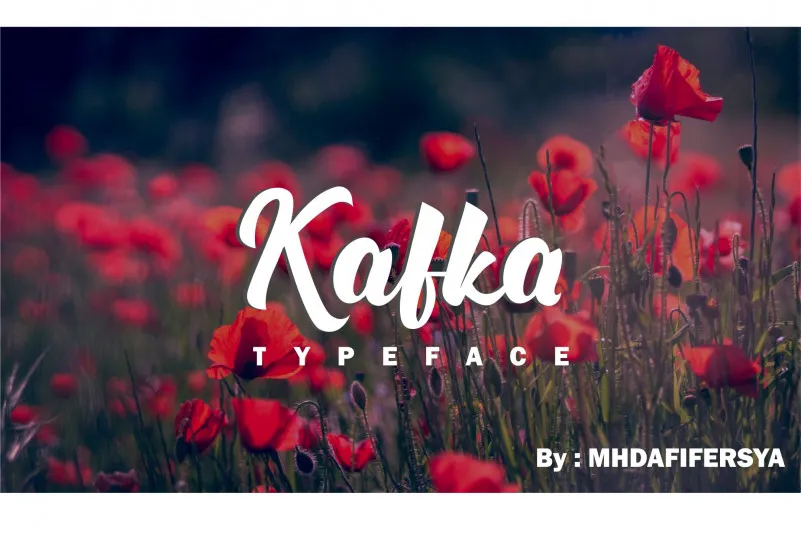
Kafka Script Font é uma tipografia em estilo script que se destaca pela sua força e elegância. Desenvolvida pelo designer mhdafifersya, ela se apresenta como um tipo de tipo com aparência limpa e rústica. Ideal tanto para criação de logotipos quanto para design de materiais promocionais ou arte impressa, esta fonte também é perfeitamente adequada para criações de camisas personalizadas, marcas de marca, cartões de nome e até mesmo identidades pessoais. Com sua simplicidade e vigor distintivos, Kafka Script Font se destaca como uma opção versátil para quem busca um estilo elegante e moderno em seus projetos visuais.